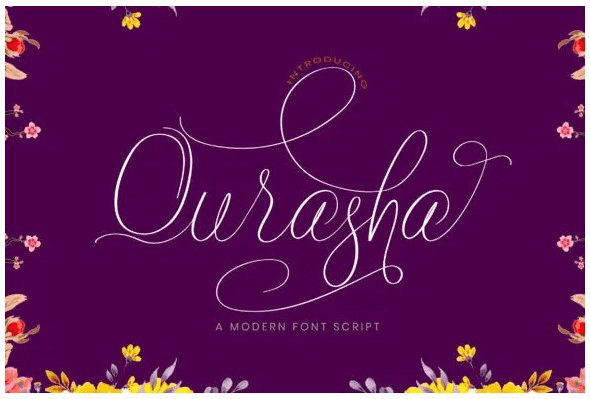
Название: Qurasha Font
Qurasha - это тонкий, элегантный и современный шрифт для письма.
У него красивые и хорошо сбалансированные характеры. Кураша отличается изменяющейся базовой линией, плавными линиями, великолепными глифами и потрясающими альтернативами. Добавьте его к вашим самым творческим идеям и обратите внимание, как он оживляет их!